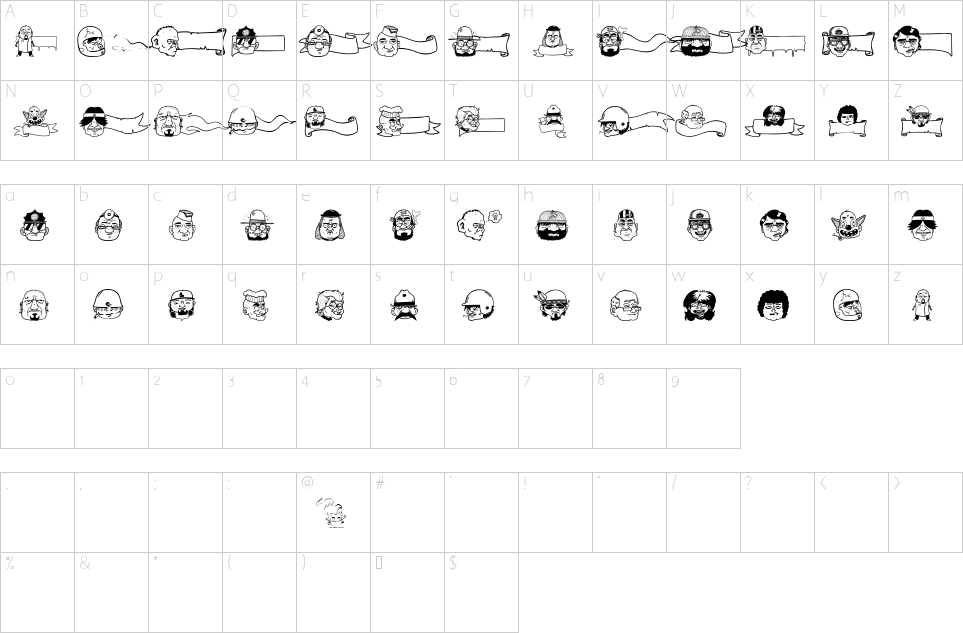
A fonte ‘Meaning Of Life Font’ é uma criação criativa do designer dcoxy, disponível gratuitamente tanto para Windows quanto para Mac. Esta fonte carrega consigo um significado aprofundado sobre a pergunta fundamental ‘o que é a vida’, algo que certamente despertará a curiosidade de qualquer usuário. Com um design que captura a essência da pergunta filosófica, ‘Meaning Of Life Font’ é mais que apenas uma ferramenta de escrita. Serve como um lembrete constante de que a busca por significado continua sendo uma parte importante da nossa jornada. Com seu download já realizados mais de 7.629 vezes, é evidente que essa fonte é uma escolha inteligente para aqueles que buscam adicionar um toque especial à sua obra de arte digital.